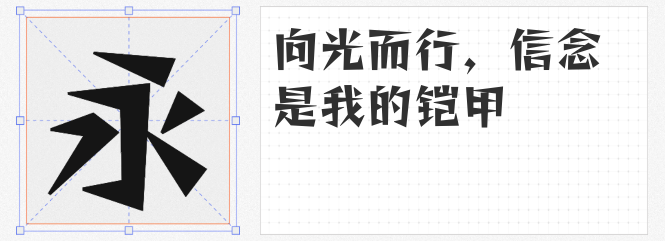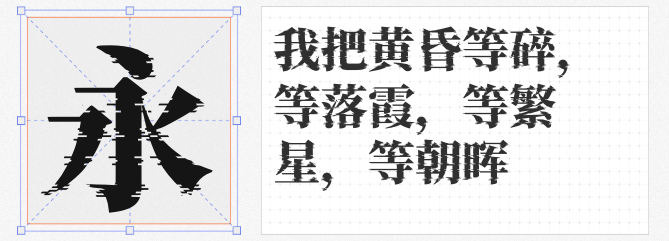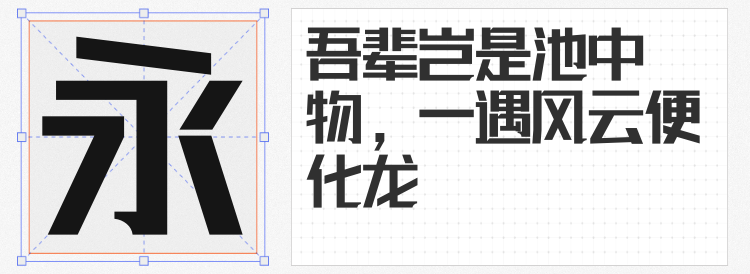
对于设计师而言,字体不仅是信息的载体,更是视觉表达的灵魂。然而,商用字体昂贵的授权费常常让人望而却步。今天推荐四款免费商用且风格炸裂的字体——它们兼顾实用性与设计感,覆盖从赛博朋克到现代简约的多元场景,堪称设计打工人的“字体救星”!
基于思源宋体CN的强大字库,猫啃网故障宋完美继承了其“字数管饱”的优势,彻底告别缺字焦虑。更令人惊喜的是,它在保留宋体典雅骨架的同时,融入了故障艺术特有的像素撕裂与色彩错位效果,让古典韵味与数字未来感奇妙交融。无论是科技感海报标题,还是品牌视觉中的文化符号,这款字体都能轻松驾驭。
如果说故障宋是“文化混血儿”,那么猫啃网故障黑则是纯粹的赛博朋克代言人。这款字体以粗犷的笔画与尖锐的棱角构建出科幻电影般的视觉冲击,霓虹灯管般的扭曲效果与金属质感细节,仿佛直接从《银翼杀手》的场景中跃出。无论是游戏UI、音乐专辑封面,还是潮牌宣传物料,它都能瞬间点燃观众的肾上腺素。
由日本Fontworks开源字体改造而来的雷盖体,填补了中文免费字体中“日系潮流风”的空白。设计师在保留原字体俏皮笔触的同时,针对性补全了简体汉字,并对部分字形进行国标化调整。这款字体自带漫画般的跃动感,笔画末端的小弧度如同音符般轻盈,非常适合餐饮品牌、二次元周边或手账类设计,让作品瞬间元气满满。
作为一款创意黑体,联盟起艺卢帅正锐黑体用极简的线条诠释了“少即是多”的设计哲学。四角锋利如刀刻,笔画粗细对比鲜明,既保留了黑体的严谨结构,又通过微妙的斜切处理赋予字体动态张力。无论是科技产品海报、建筑空间导视,还是极简风格的品牌LOGO,它都能以低调的锋芒撑起画面焦点。